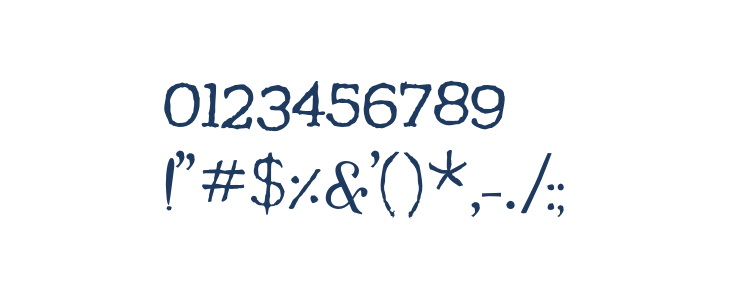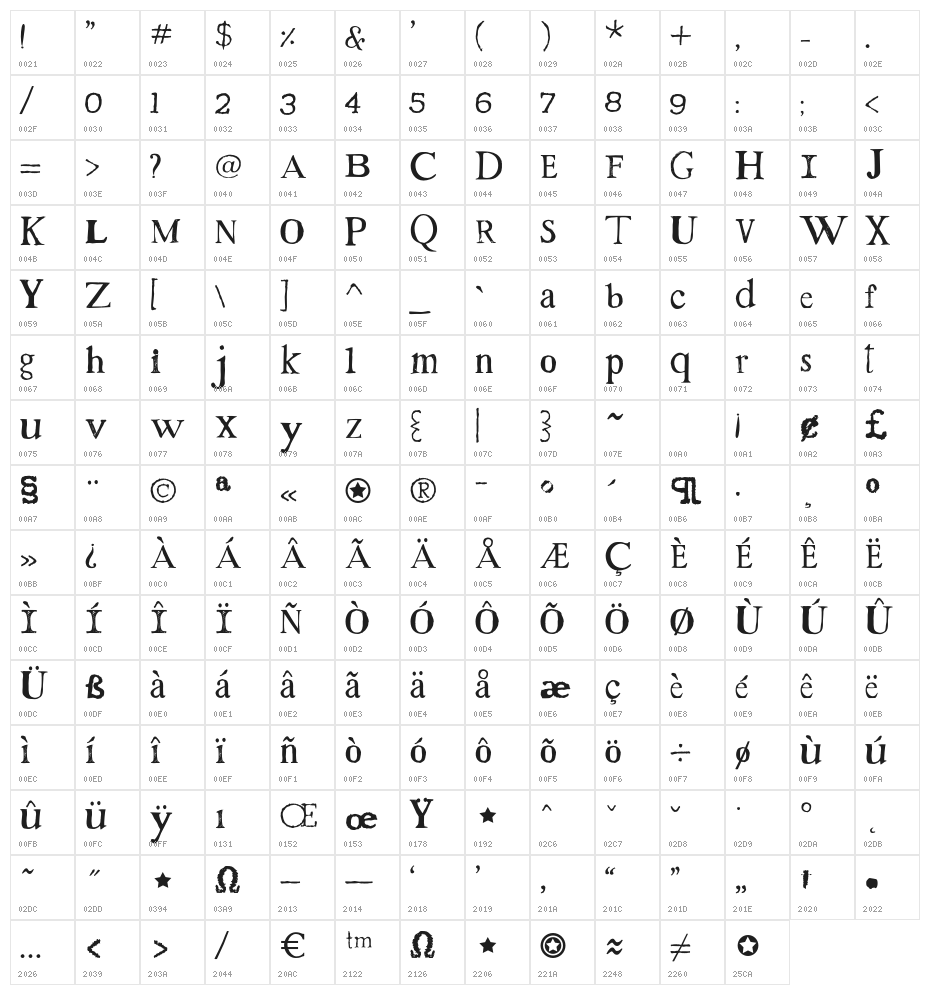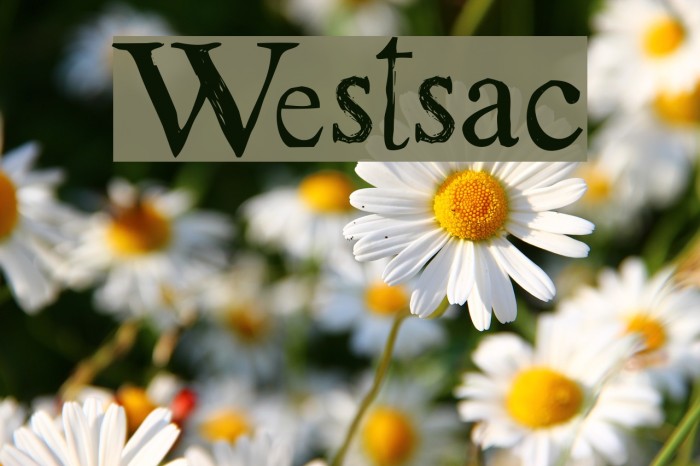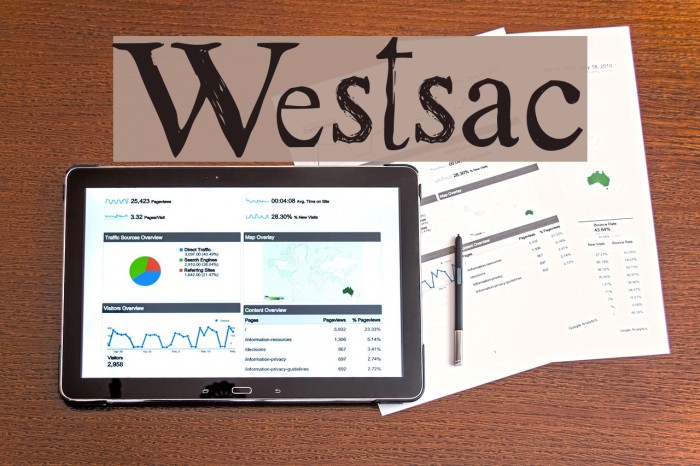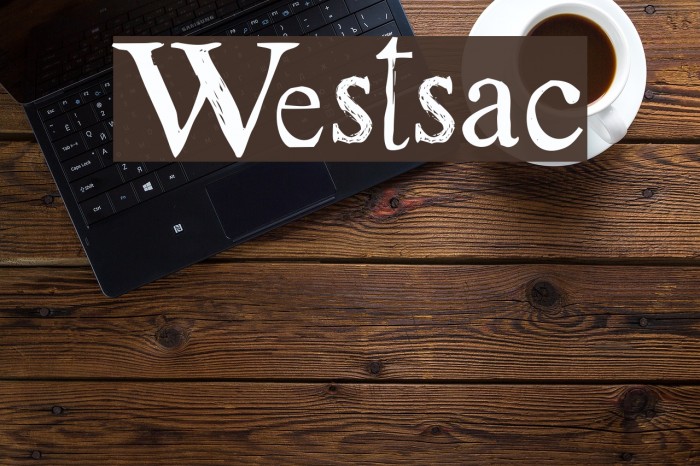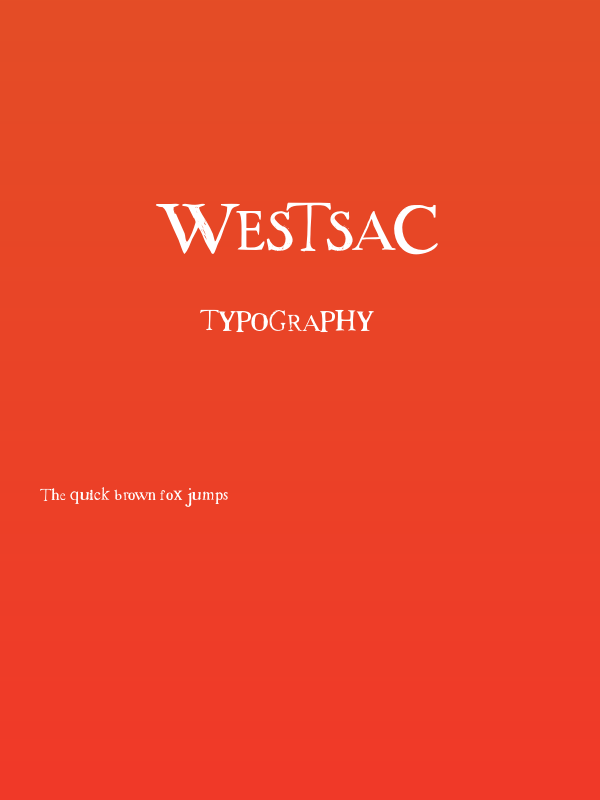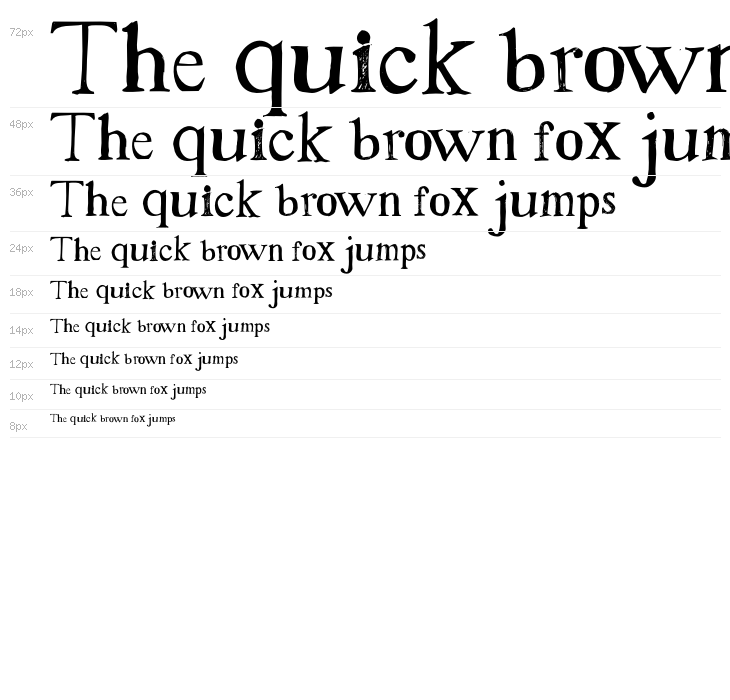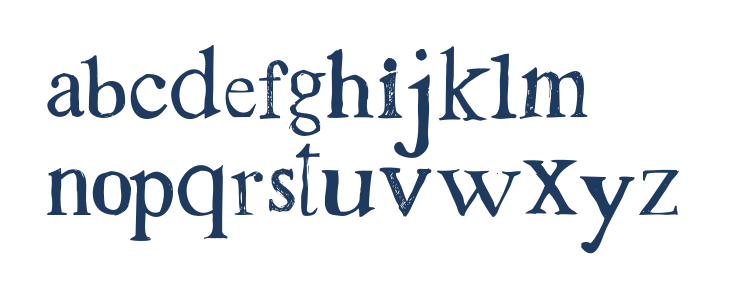
Westsac Font
✎ Retro
| Caz de utilizare | Logos, Headlines, Artistic projects |
| Proiecte propuse | Ideal for vintage-themed posters, rustic branding, book covers, and artistic projects that require a handcrafted look. |